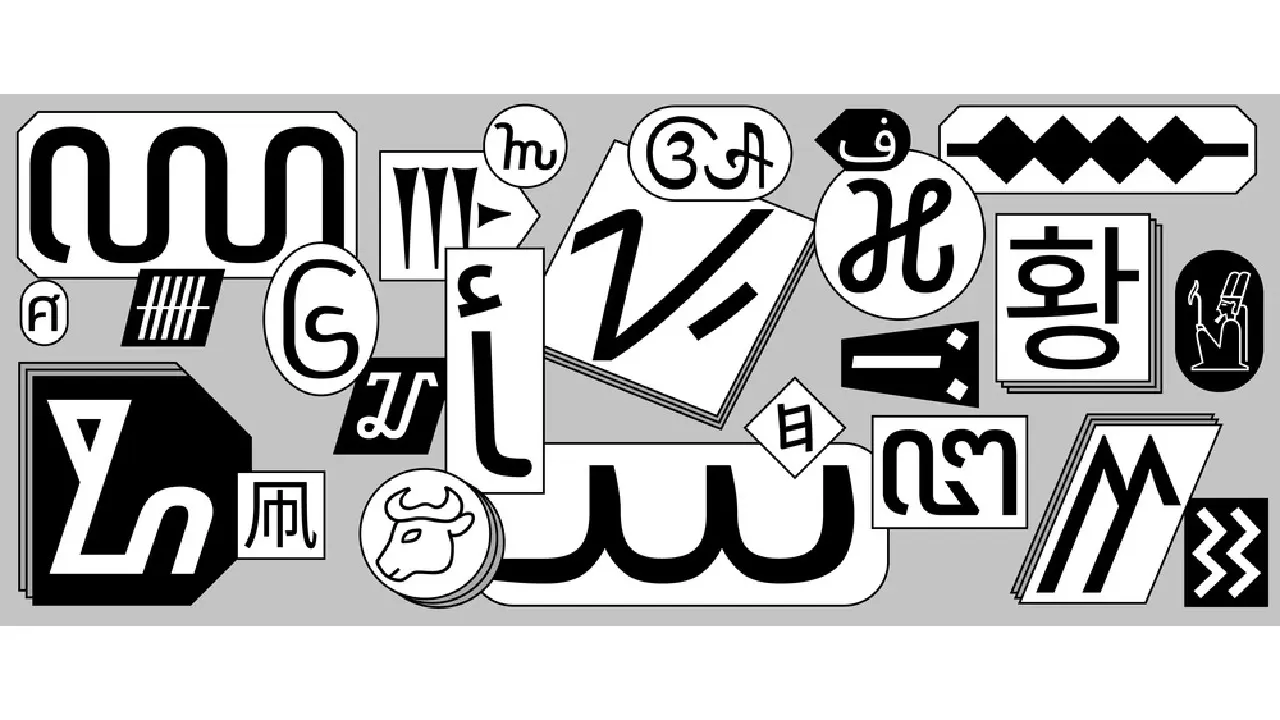
Untuk hal ini, keluarga Noto font yang tersedia secara gratis dari Google Fonts mendukung literasi untuk ratusan bahasa.
"Bangsa Cherokee, dengan sekitar 20.000 penutur, menggunakan Noto di ponsel untuk mengirim pesan teks, email, dan mengajar bahasa mereka di AS. Noto digunakan setiap hari untuk bahasa Tibet, jutaan pengguna Afrika, dan ratusan bahasa Asia," ujar Susanna Zaraysky, Content Strategist, Material Design di Google dikutip dari keterangan perusahaan.
Susanna juga menyoroti pemerintah British Columbia di Kanada, dengan populasi 5 juta orang, ingin mencakup semua bahasa mereka, termasuk bahasa asli, dalam satu font dan menggabungkan Noto Sans + Noto Sans Canadian Aborigin menjadi satu font, yakni font BC Sans.
Noto menawarkan font untuk 146 skrip (sistem penulisan) dan lebih dari 800 bahasa, dan membuka pintu untuk membaca dan menulis bagi penutur bahasa minoritas.
"Noto adalah sumber font terbesar untuk bahasa yang terancam punah," ujar Susanna lebih lanjut.
Open Source Sepenuhnya
Selaras dengan dukungan Google.org untuk Proyek Bahasa Terancam Punah dan inisiatif Google menjadi sponsor privat untuk ajang UNESCO bertajuk Language Technologies for All, proyek Noto adalah proyek font Unicode Google yang ambisius. Proyek ini bertujuan untuk terus mendukung 100 persen dari semua karakter Unicode setiap tahun dengan font yang berfungsi penuh.
Dikembangkan sejak 2012, Noto baru-baru ini juga memperbarui halamannya di GitHub. Rumah baru di github.com/notofonts memiliki satu proyek git per skrip, dengan semua sumber tersedia dalam sumber font Unified Font Object (UFO) yang didukung secara luas atau menggunakan format .glyphs.
"Kami juga memiliki sistem build on-demand baru yang dipicu segera setelah seseorang memperbarui sumber font yang menggunakan compiler 'fontmake' open source Google Fonts. Ini berarti Noto font sekarang benar-benar open source sepenuhnya, akan didokumentasikan dengan lebih baik dan tersedia untuk kontribusi lebih banyak orang," tutur Susanna